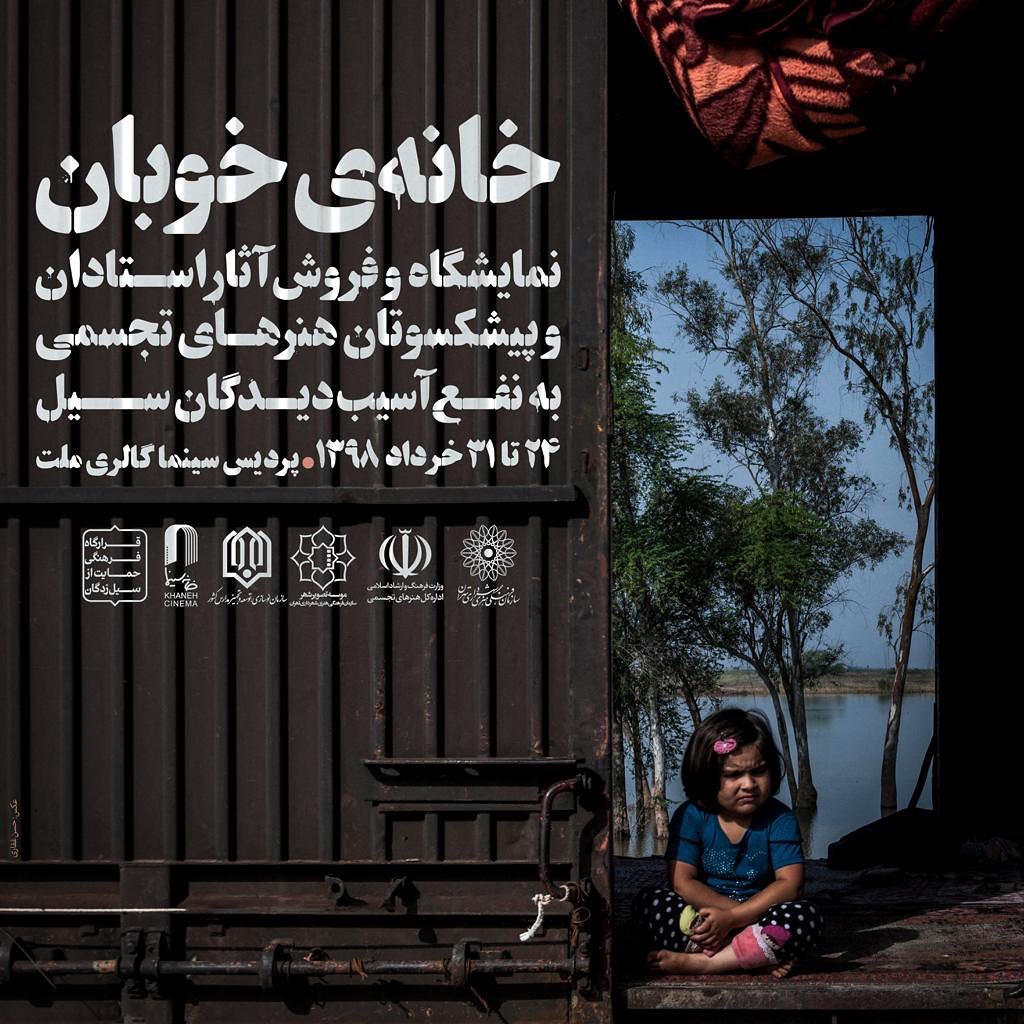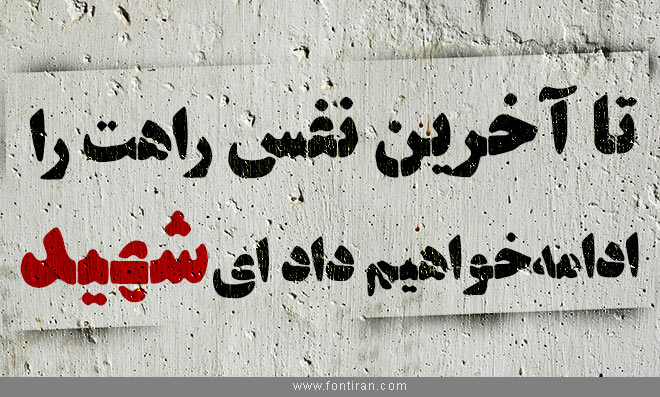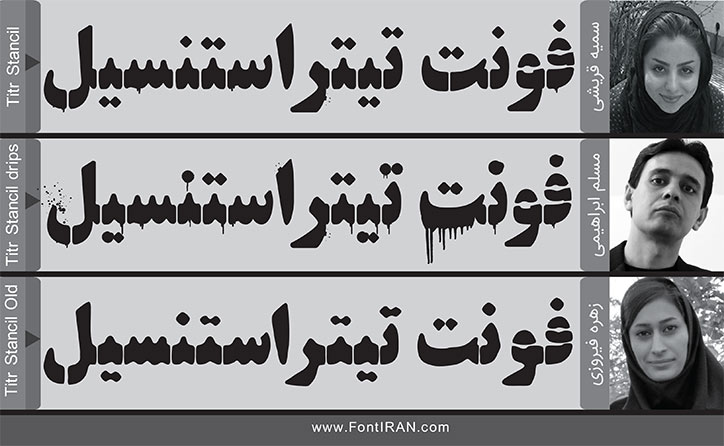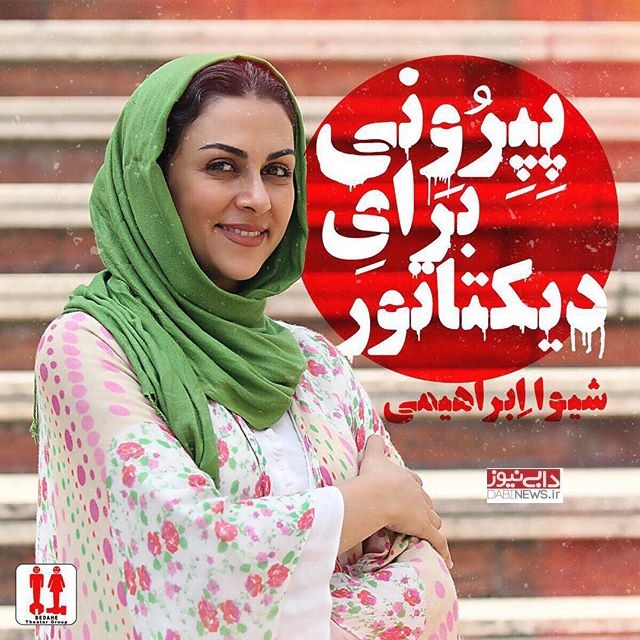
فونت تیتر استنسیل
فونت تیتر استنسیل توسط یکی از نام آشنا ترین طراحان تایپوگرافی ایجاد و ابداع گردیده است . آقای مسلم ابراهیمی بنیانگذار سایت فونت ایران این قلم را در 3 استایل متفاوت طراحی کرده است. این تایپ فیس پشتیبانی از اعداد فارسی را هم به دنبال دارد. به وفور به کلیشه استنسیل تبدیل و بر دیوارهای ایران اسپری گردیده. از شعار نویسی های دوران انقلاب گرفته تا تبلیغات دیواری کسب و کارهای کوچک. به همین علت برخی از طراحان ممکن است بخواهند در طرح های خود چنین اتمسفری و فضای حسی را ایجاد کنند.
این قلم مناسب برای جذب نگاه مخاطبین به خود می باشد چرا که با دارا بودن ویژگی نمایشی و تزئینی خود به دنبال جذب نگاه مخاطبین به خود می باشد. شما با خرید این محصول سه فونت فارسی با نام های : Titr Stancil ، Titr Stancil drips و Titr Stancil old (و تعدادی فونت انگلیسی رایگان سبک استنسیل و گرافیتی) دریافت می کنید.
Titr Stancil : ساده ترین فونت این مجموعه است این قلم در واقع همان تیتر است که پُل ها و انفصال های استنسیل به آن اضافه شده و مقدار نویز کمی در افکت آن وجود دارد.
Titr Stancil drips: در سبک drips یا همان چکه نویز و افکت فراوان وجود دارد و تعداد زیادی از حروف افکت شرره کردن رنگ و اسپری را نشان می دهند.
Titr Stancil old: در استایل کهنه با اینکه اصلا افکت شره اسپری و نویز وجود ندارد اما چون کاملا با دست استنسیل حروف بازسازی شده حالت واقعی تری از شابلون های قدیمی را به نمایش میگذارد.